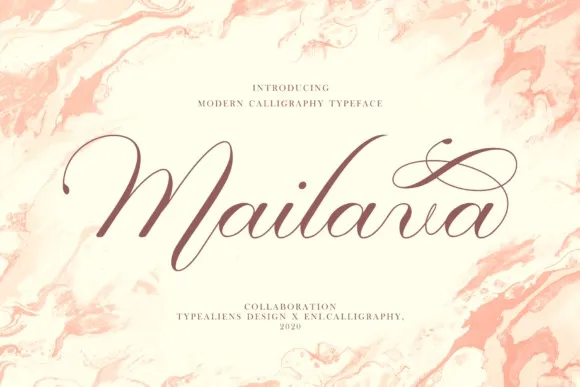
Esta é uma fonte script romântica e naturalmente fluida criada pelo designer typealiens. Ela traz aos usuários a conveniência do PUA (Unicode) encodado, permitindo um acesso fácil para todas as gílias e espirais. Este tipo de letra oferece linhas suaves e linhas variáveis em baseline, adornos e alternativas de traço excepcionalmente belas e deslumbrantes. Não apenas mantém suas influências classicamente alinhadas na caligrafia, mas também se move para um contemporâneo e fresco design. Adorável para qualquer projeto que você possa imaginar, essa fonte deixa seus trabalhos a um nível superior. Ela é perfeita tanto para aqueles desejando algo romântico e autêntico quanto para aqueles buscando um look atualizado e moderno. É uma escolha incrível para tornar seu design único e personalizado, reforçando ainda mais sua originalidade e elegância. Descubra o amor por esta fonte e veja como ela pode transformar seus projetos de acordo com suas necessidades e visão pessoal.